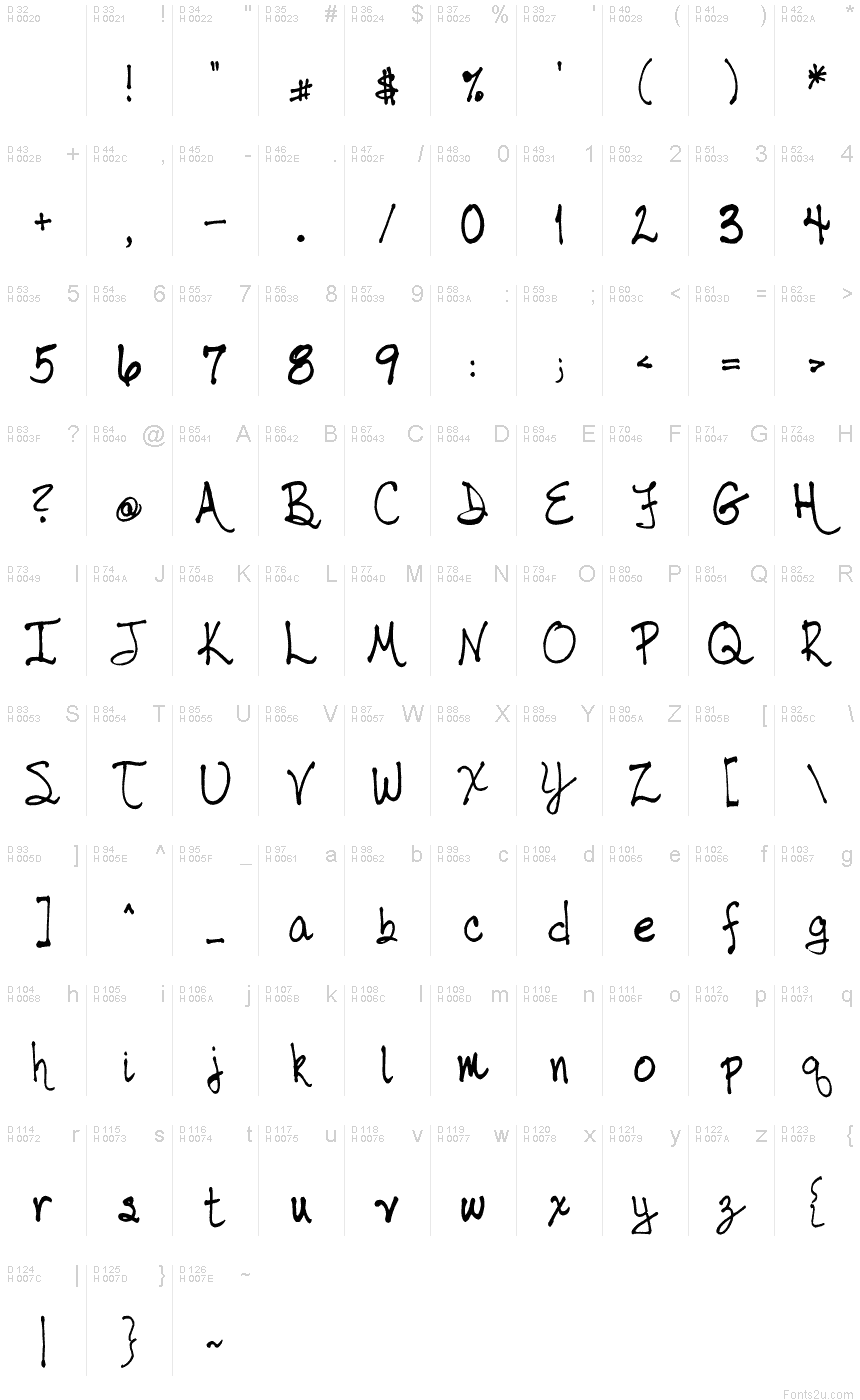
Tabor Handwriting je bezplatné písmo psané rukou s uvolněným rytmem, jako by bylo kreslené fixou, a osobitým dojmem. Písmena sázejí na silné, zaoblené tahy a mírně nepravidelné spoje, s širokými křivkami a ležérním švihem, díky němuž působí spíše hřejivě než učesaně.
Hodí se do menu kaváren, nadpisů ve scrapbookech, na přáníčka, neformální branding nebo plakáty, kde by bezplatné písmo mělo působit lidsky, nikoliv vybroušeně. Použijte ho na krátké texty na obalech, příspěvky na sociální sítě nebo titulky v denících – hustý rukopisný tok dodává krátkým slovům přátelský, ručně tvořený vzhled.